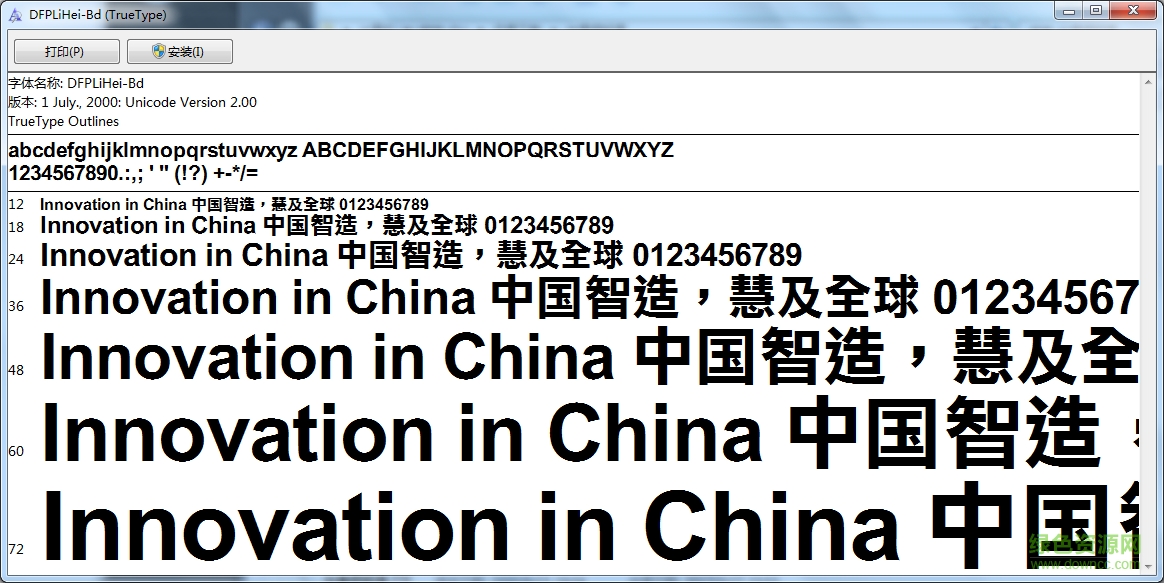
dfplihei-bd-普通字體又叫華康儷粗黑,是一款非常漂亮的黑體字體,橫豎筆畫(huà)粗細(xì)基本一致,整齊端正,井然規(guī)范,可以用于表現(xiàn)力量感,需要的小伙伴們快來(lái)下載吧!
【黑體】
1.無(wú)襯線的黑體給人一種干凈,簡(jiǎn)約的感覺(jué),同時(shí)還帶著輕松休閑的氣氛。
2.黑體給人的感覺(jué)是時(shí)尚簡(jiǎn)約,優(yōu)雅端莊。常用于高端品牌或發(fā)布會(huì)現(xiàn)場(chǎng)等。